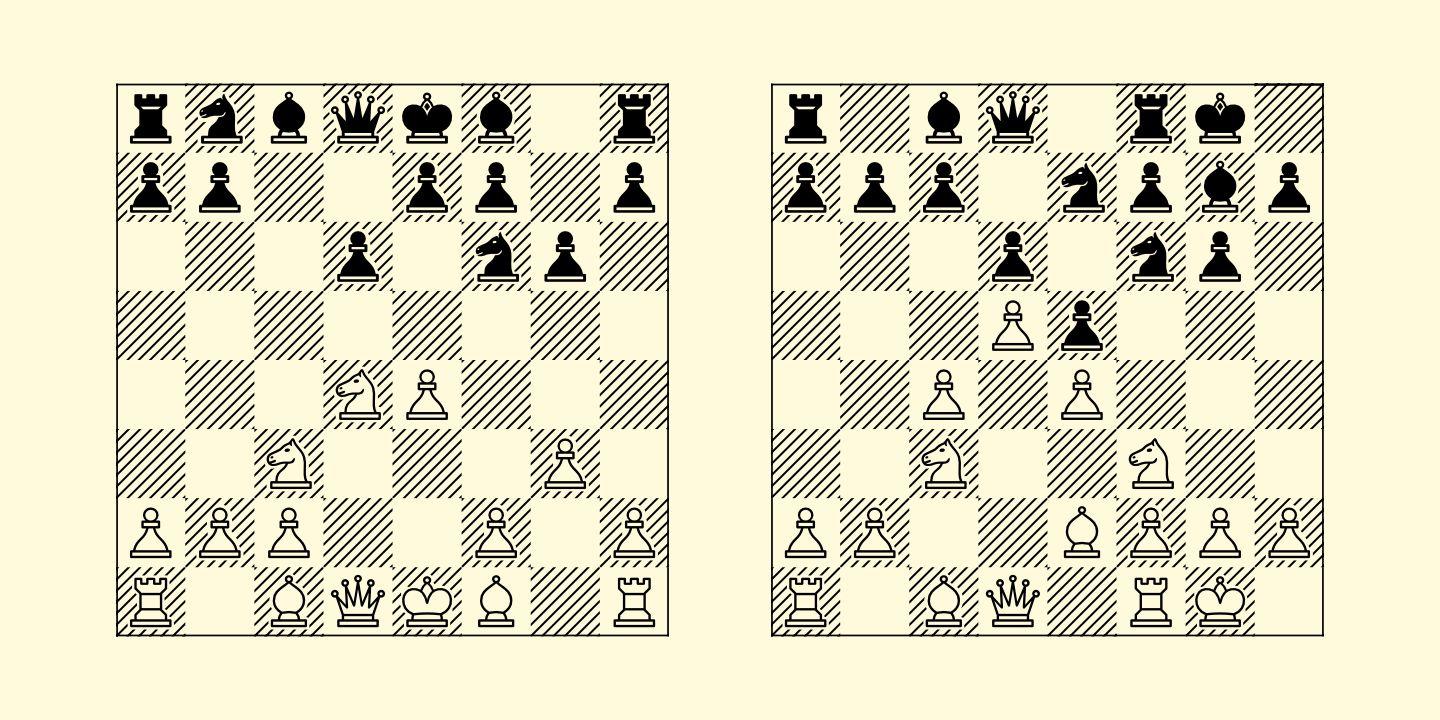
Chessnota Font
Description de Chessnota Font
Chessnota est une police adaptée à la conception de schémas d’échecs. Il comprend des images graphiques originales de pièces d’échecs ainsi que de dames. Des pièces plus petites sont placées au niveau de la chaîne de texte afin de remplacer les lettres dans la notation échiquéenne. Il peut être utilisé pour l’impression de magazines d’échecs, de livres, dans n’importe quelle conception de schémas sur des sites Web.